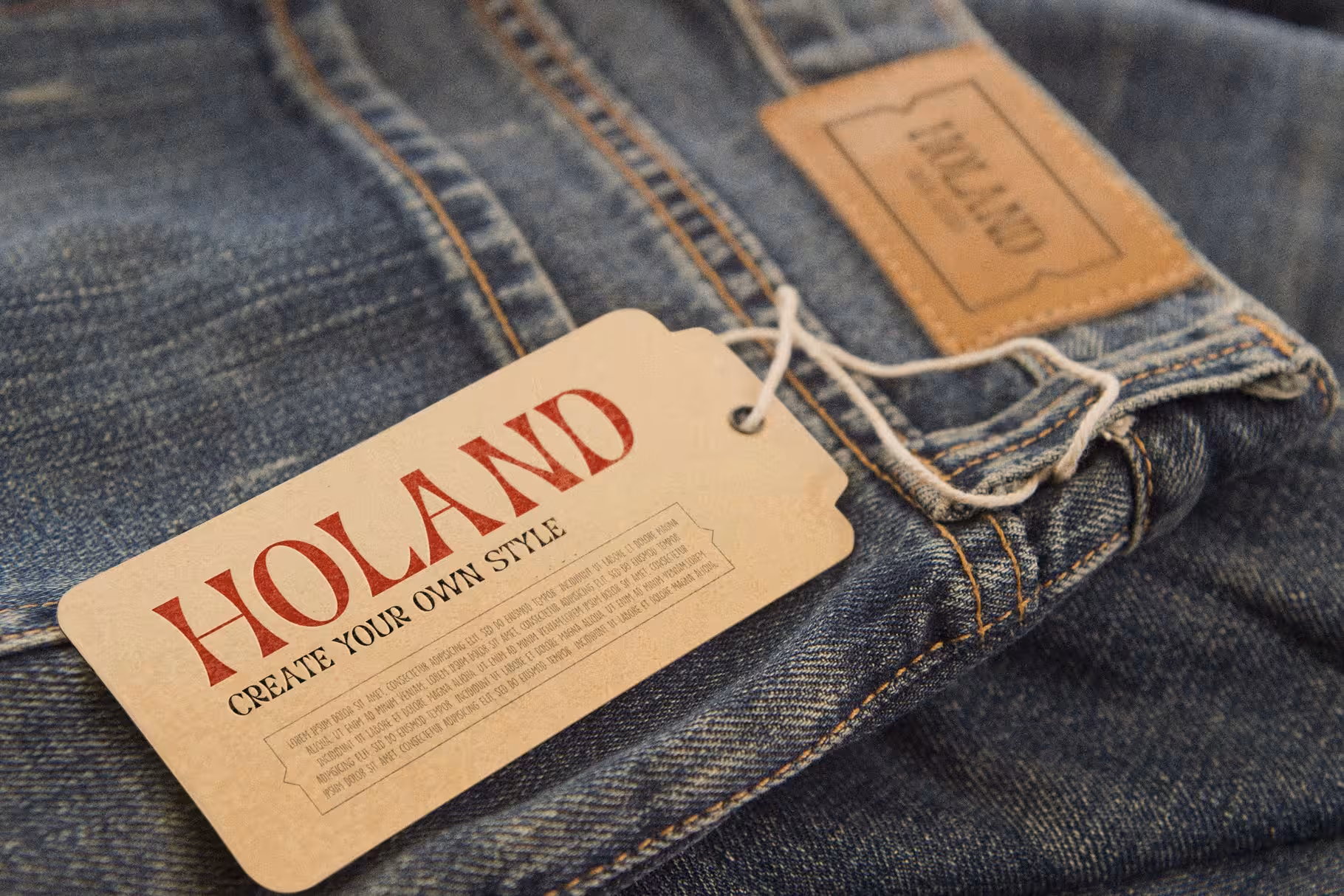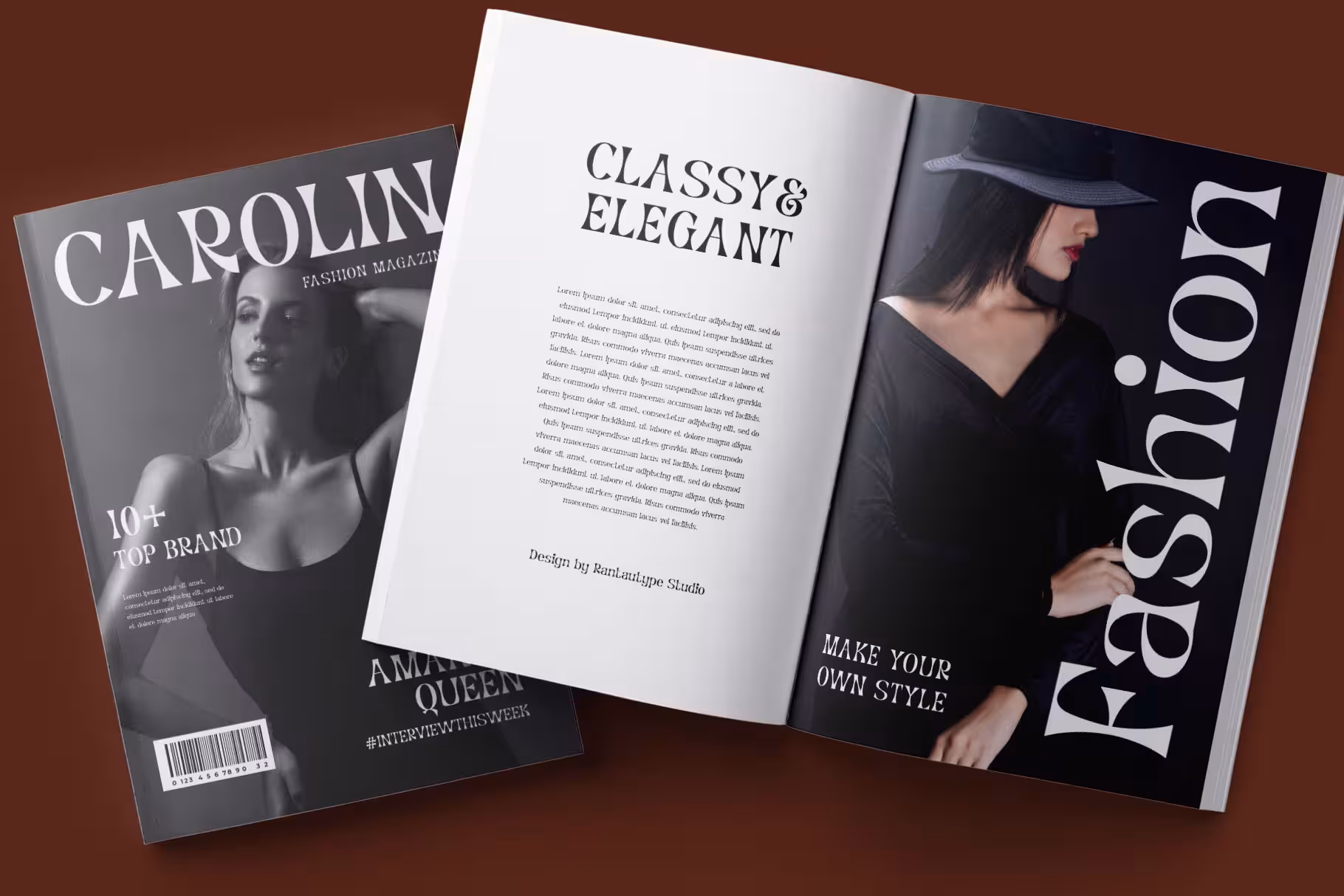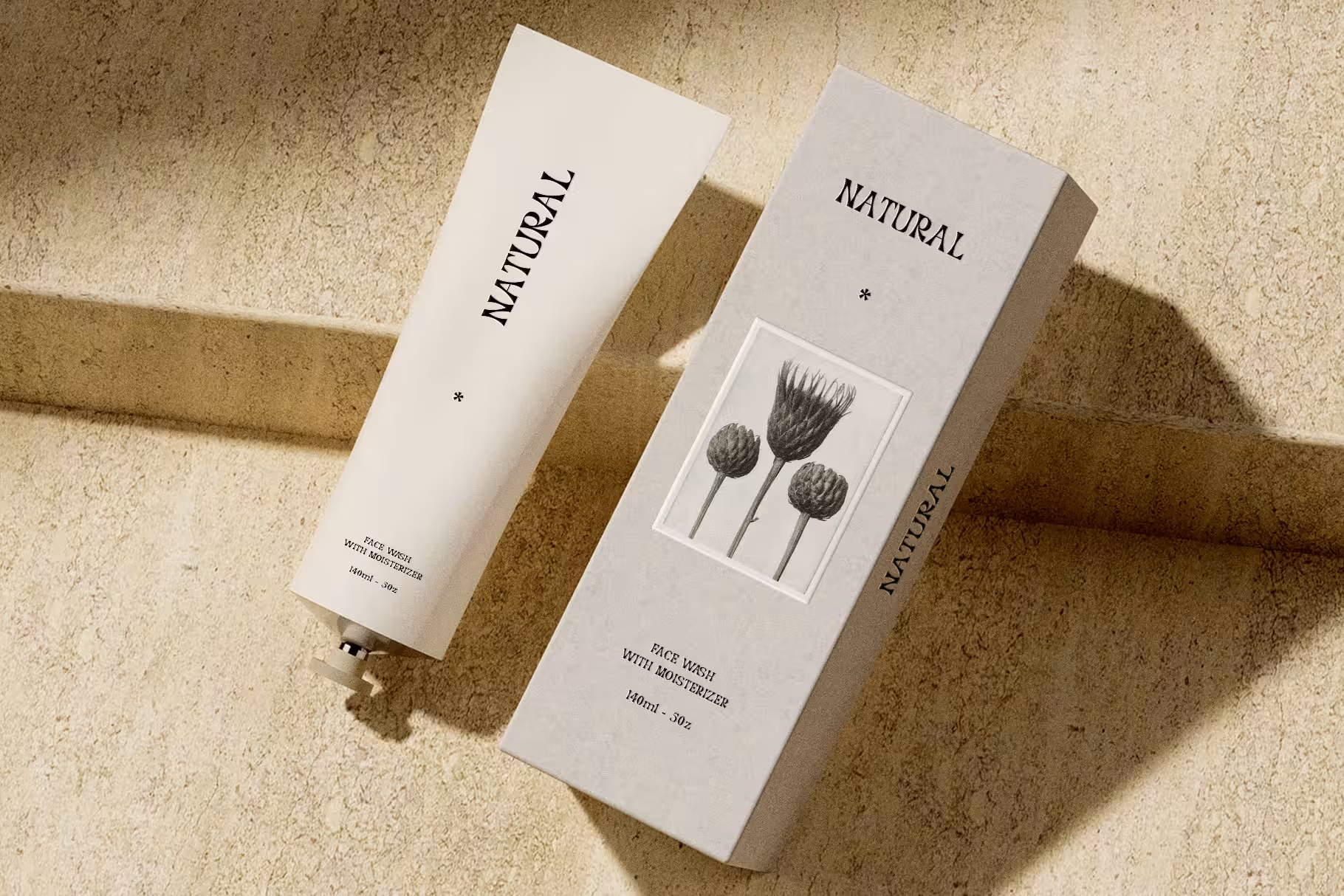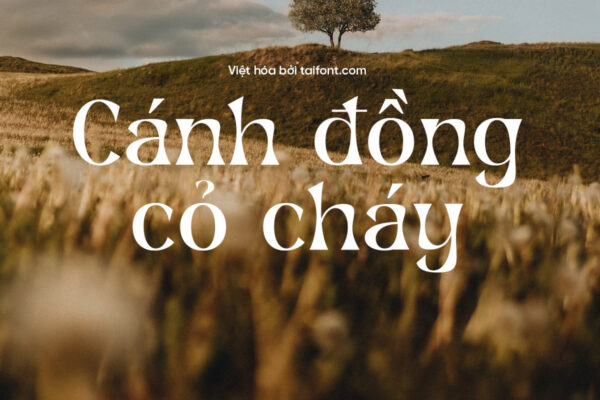
Giới thiệu về Font TF Cenoria Việt hóa
TF Cenoria Việt hóa là một font chữ mang đậm phong cách vintage (hoài cổ) và đầy tinh tế, toát lên vẻ đẹp sang trọng, quý phái và vượt thời gian. Với những đường nét được thiết kế tỉ mỉ, đôi khi có những chi tiết độc đáo gợi nhớ về các font chữ kinh điển, Cenoria là lựa chọn lý tưởng để tạo nên sự độc đáo và đẳng cấp cho các thiết kế.
Font này là lựa chọn tuyệt vời để bạn thể hiện sự sáng tạo và tạo không khí hoài cổ, sang trọng cho các ấn phẩm của mình:
- Thiết kế thời trang: Hoàn hảo cho các thương hiệu thời trang cao cấp, đặc biệt là những bộ sưu tập mang phong cách cổ điển, thanh lịch. Font này có thể dùng trên nhãn mác sản phẩm, lookbook, hoặc các chiến dịch quảng bá, giúp truyền tải vẻ đẹp tinh tế, sang trọng và độc đáo của trang phục.
- Thiết kế mỹ phẩm: Lý tưởng để sử dụng trên bao bì sản phẩm, catalogue, hoặc các chiến dịch marketing. Cenoria giúp khẳng định chất lượng, sự sang trọng và giá trị vượt thời gian của thương hiệu mỹ phẩm, thu hút khách hàng tìm kiếm sự đẳng cấp.
- Thiết kế nước hoa: Phù hợp để in tên sản phẩm, thông tin thương hiệu trên chai lọ hoặc bao bì nước hoa. Font này sẽ giúp chai nước hoa của bạn toát lên vẻ quyến rũ, bí ẩn và đầy lôi cuốn, đúng như hương thơm mà nó mang lại.
Với TF Cenoria Việt hóa, bạn có thể dễ dàng thổi hồn vintage, sự tinh tế và sang trọng vào các thiết kế, tạo ra những sản phẩm không chỉ đẹp mắt mà còn đầy cảm xúc và sức hút đặc biệt.